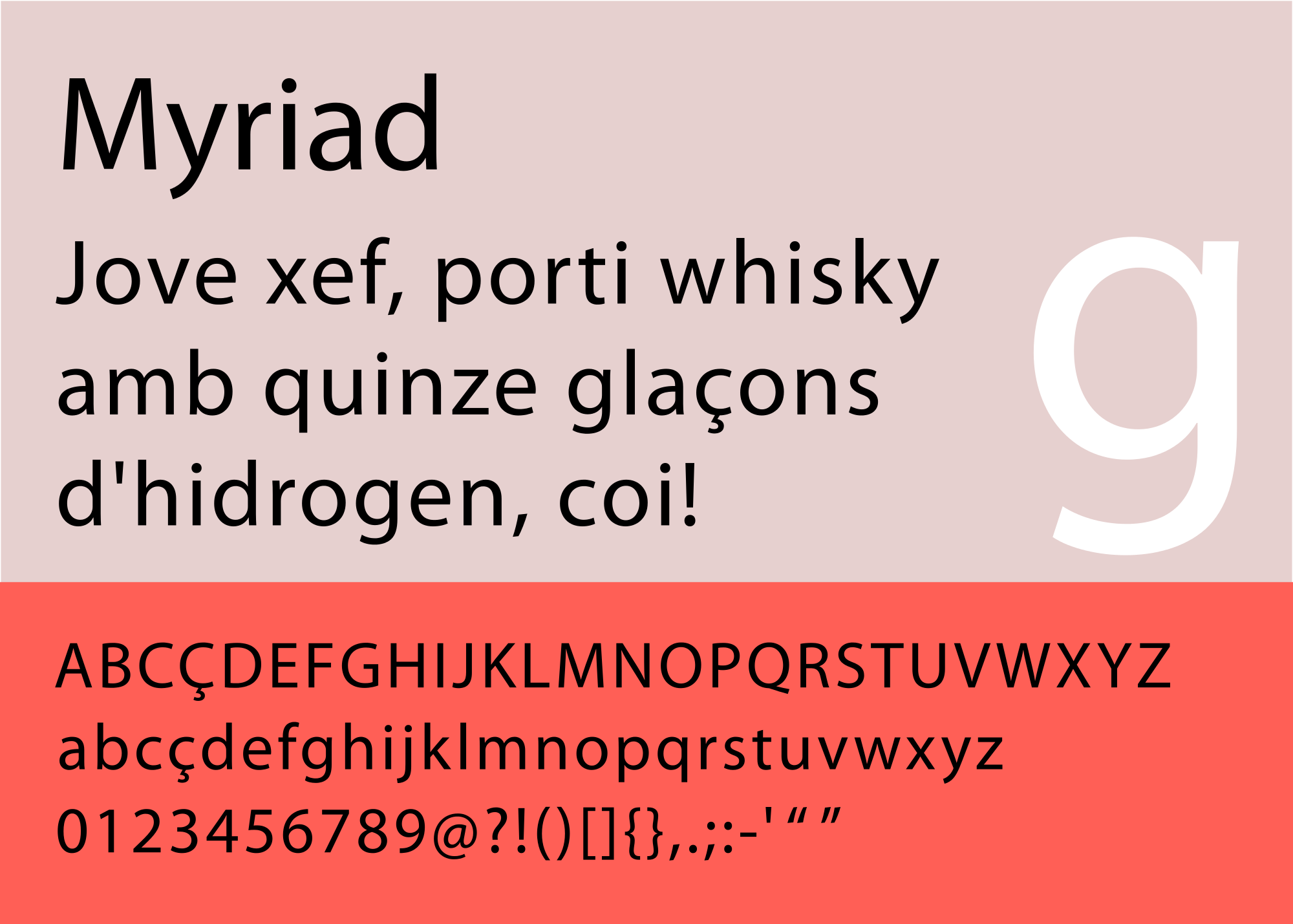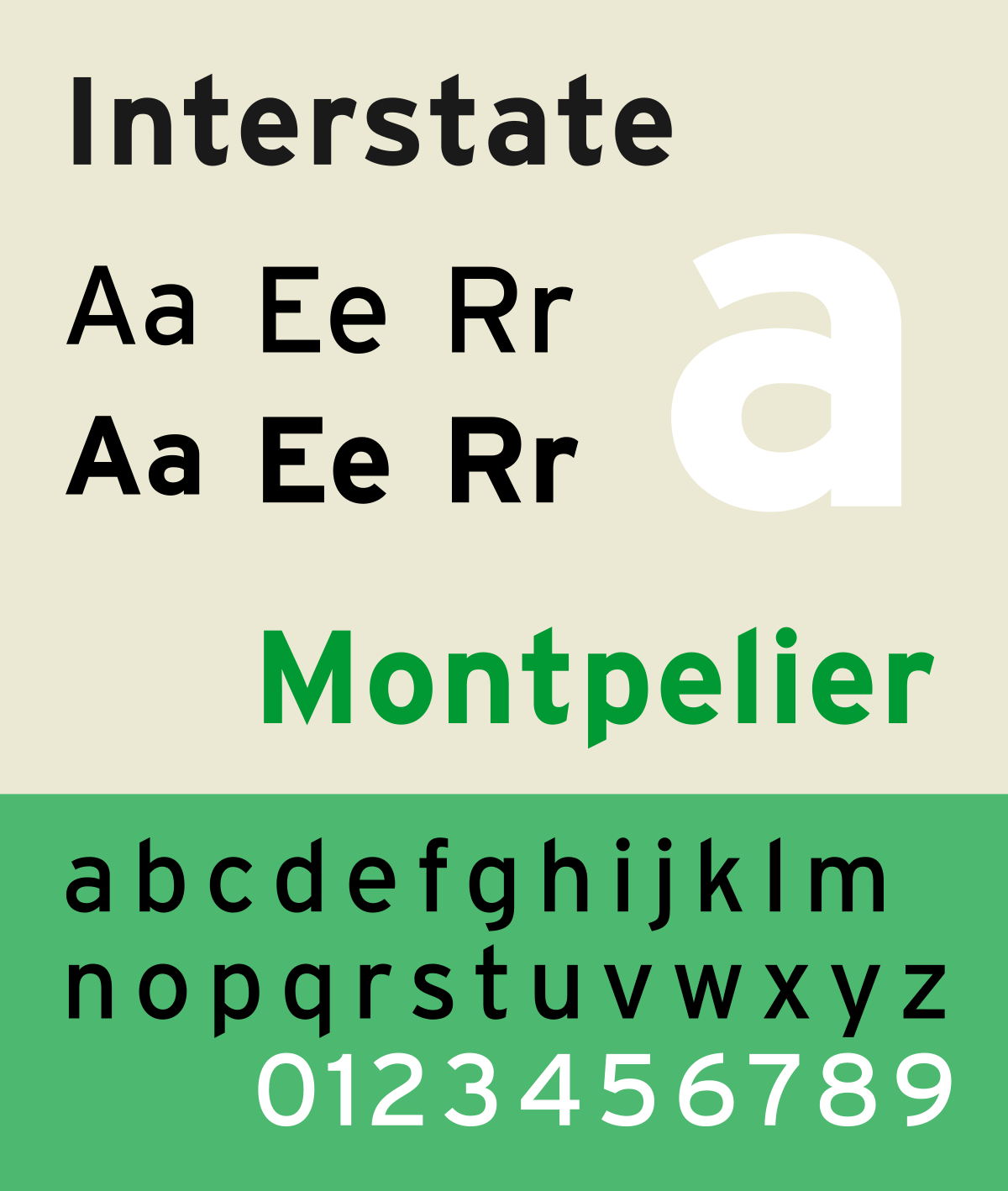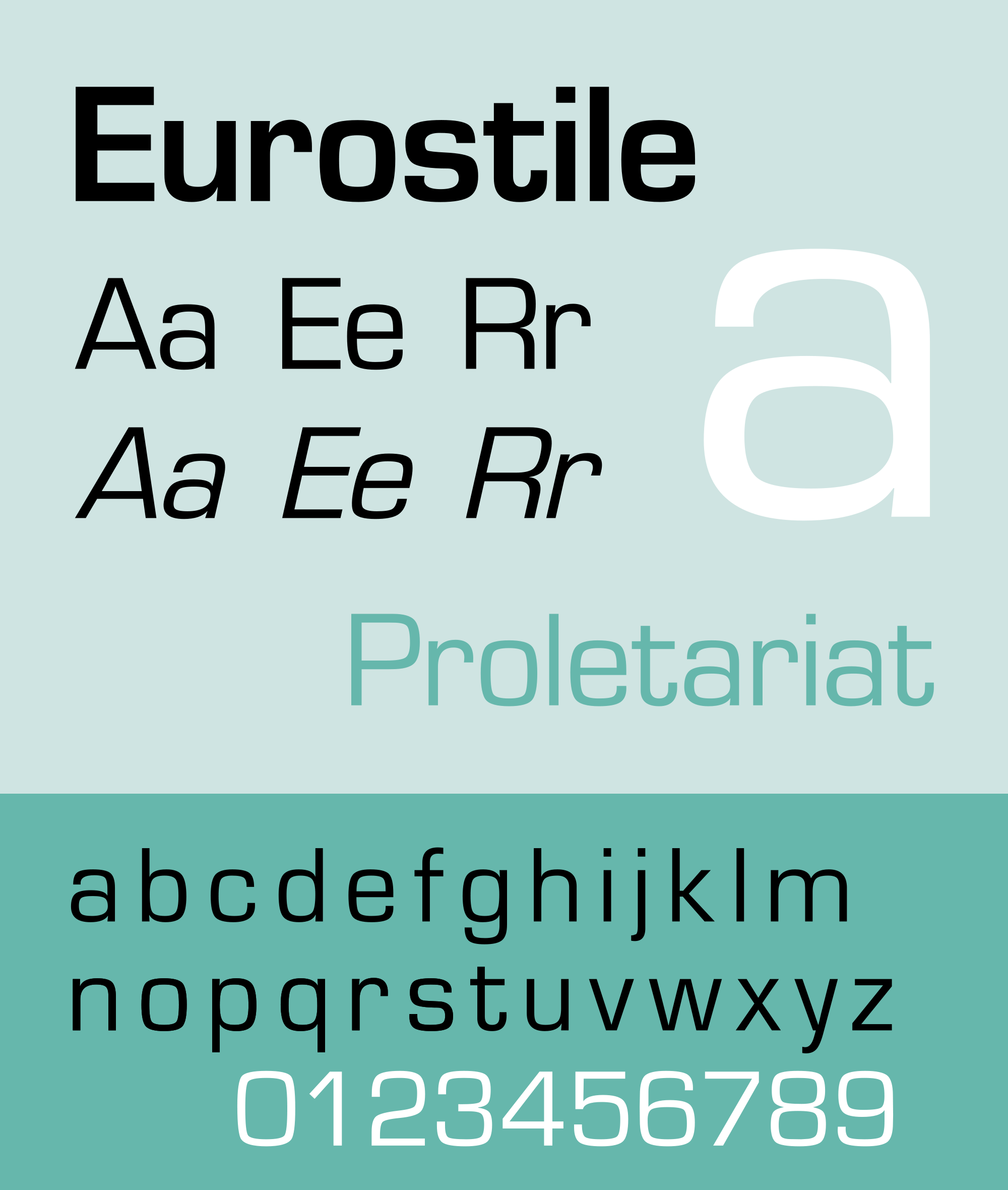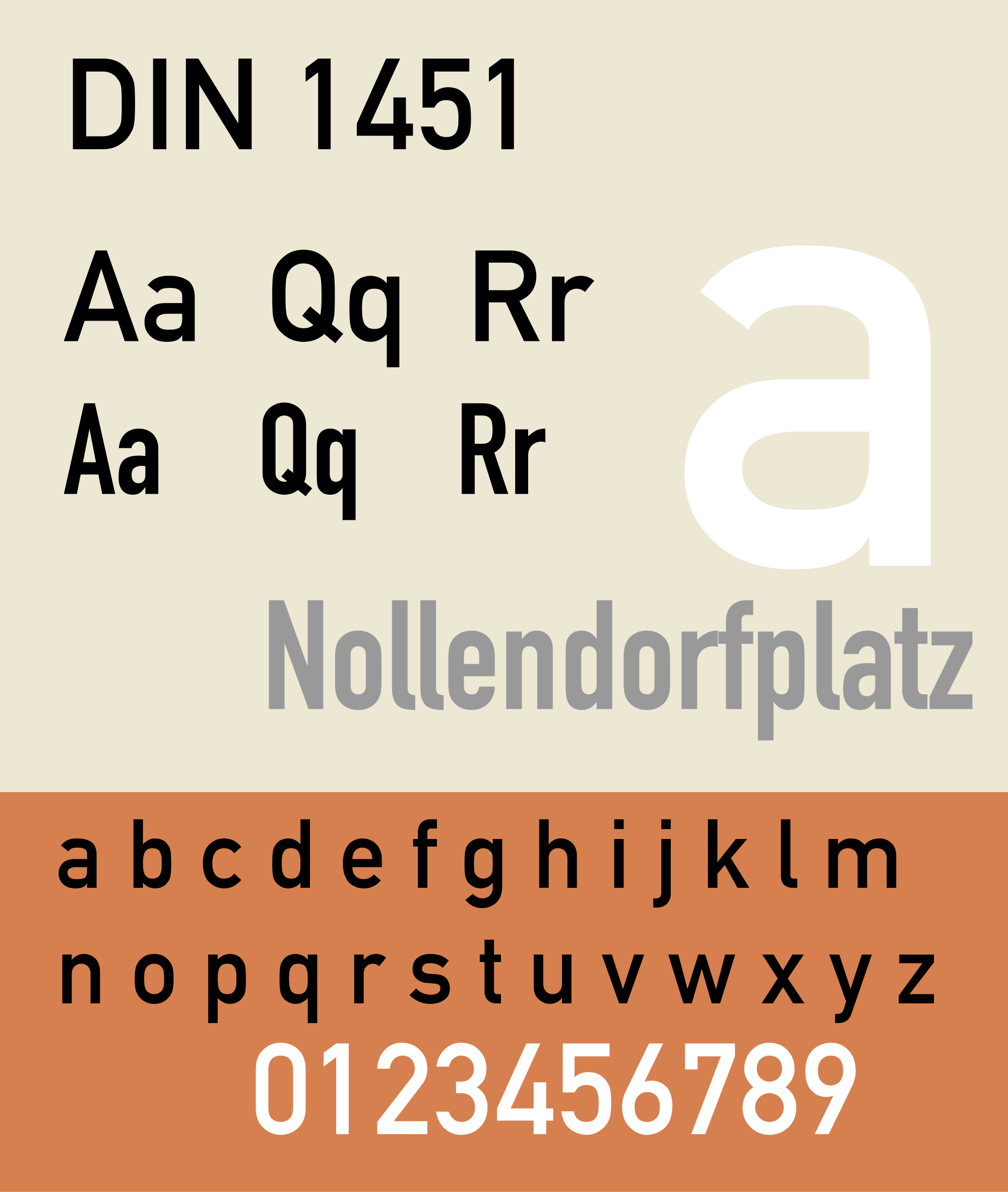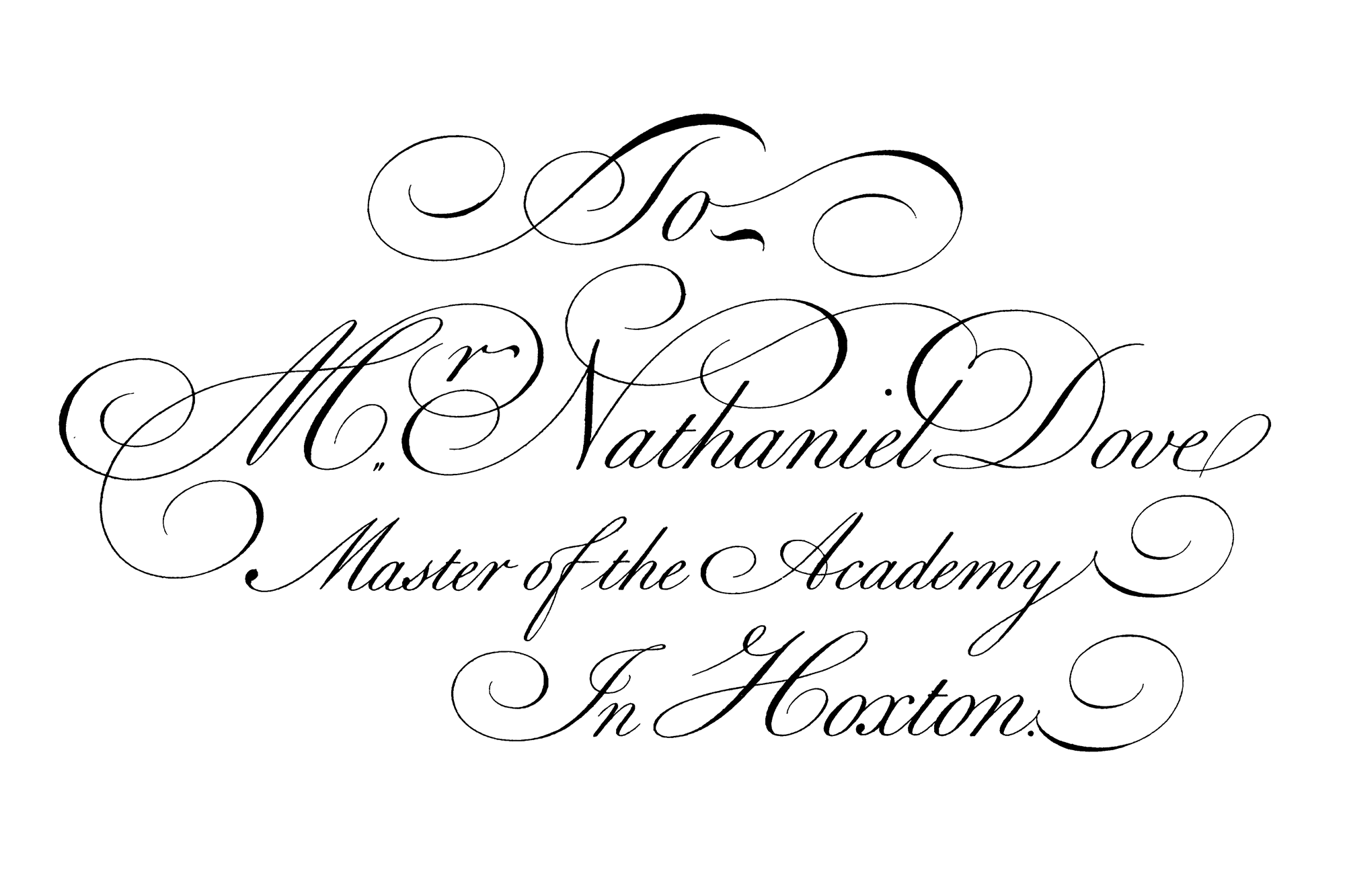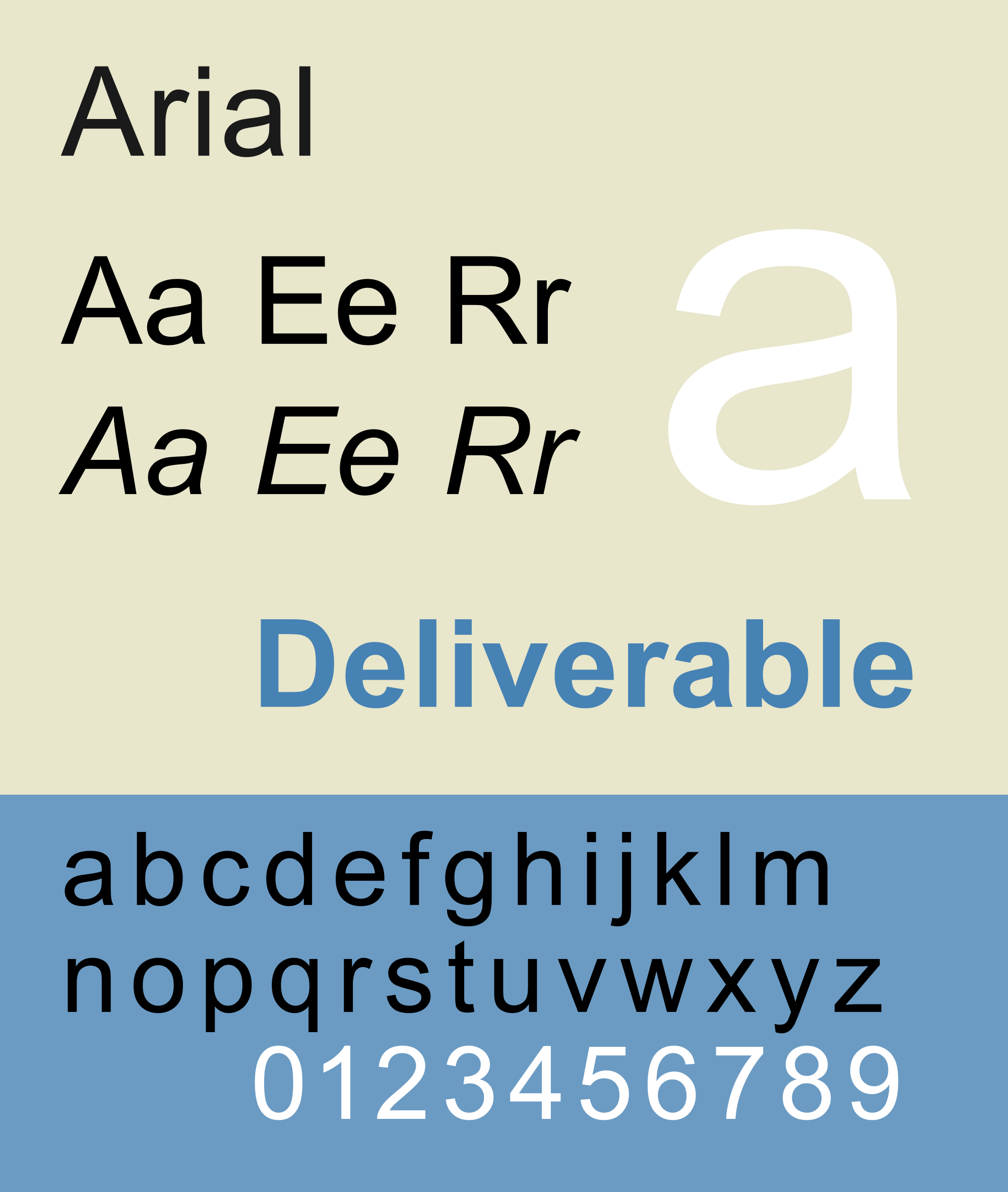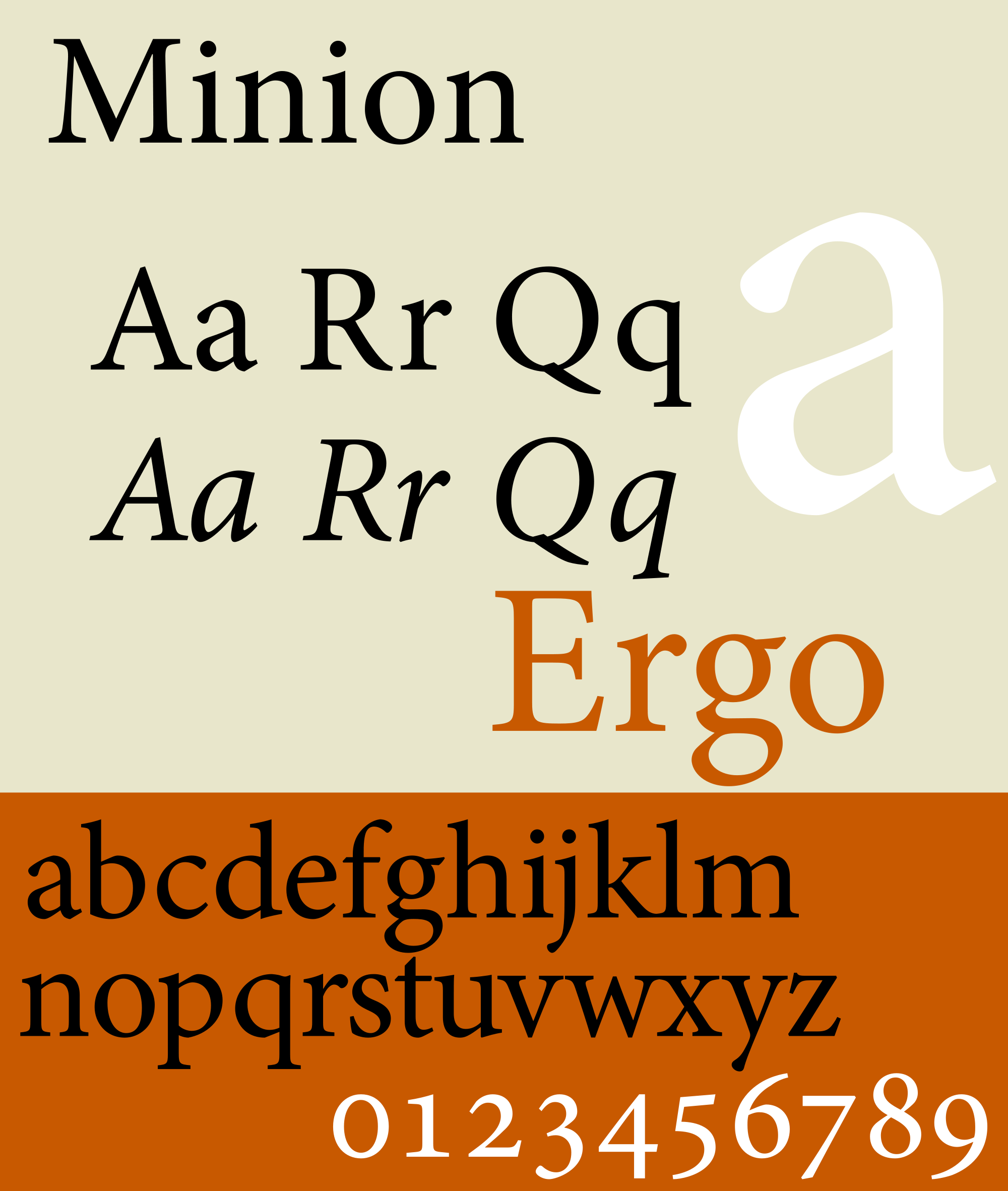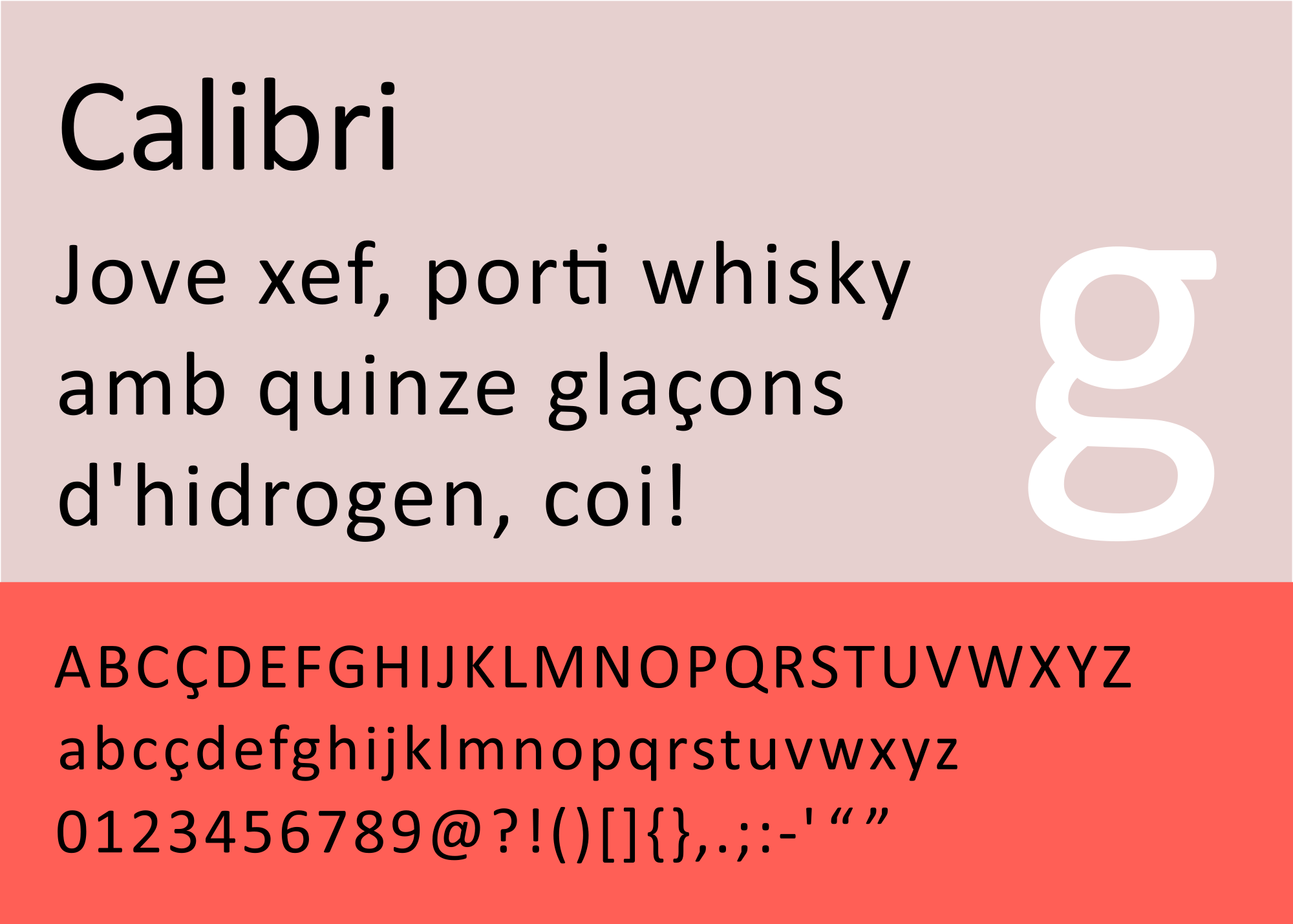
Las 25 tipografías más utilizadas en publicidad
Hay quien dice que un diseño web sin tipografía es un diseño a medias. Pero también se corre el riesgo de elegir la letra incorrecta y estropear todo el diseño. Por ello seguro que te interesa esta selección de las 25 tipografías más utilizadas en publicidad.
No siempre es fácil saber cuál elegir en cada momento. Existen algunas prohibidas, otras recomendadas y otras estándar para diseños sencillos. Pero, ¿con cuál mejoras la apariencia visual de tu sitio web?
Cada tipografía va más allá del simple «arte del texto«. Hacen referencia a la evolución de la creatividad dentro de los diseños web simples y avanzados. Toda arquitectura necesita un apoyo. Y cada web necesita de una tipografía que sirva como apoyo creativo.
Sin embargo no debes quedarte con el concepto de que una tipografía es un mero apoyo. Puede ser la encargada de lograr el éxito en la creación de identidad de la web de la marca. Es un elemento vital, por lo que antes de elegir al azar, deberías saber cuáles son las tipografías más utilizadas en publicidad.
De esta manera podrás tener un listado con las más recomendadas y tú mismo te darás cuenta de que algunas son mucho más limpias y legibles que otras. En la simpleza está la belleza. Deja a un lado las fuentes demasiado complejas. Lo que te interesa es que sea legible.
¿Cuáles son las tipografías más utilizadas en publicidad?
1.- Helvética
tipografía Helvética
La Helvética es una de las tipografías más utilizadas en publicidad y quizás, la más conocida en todo el mundo. Creada en el año 1957 por Max Miedinger y Edouard Hoffmann para la fundición de tipografías. Fue la absoluta protagonista durante los años 60 y 70.
Cuenta con una gran variedad de variantes y es muy versátil en el mundo del diseño. Además, como te hemos dicho lo que nos interesa es dar con tipografías que sean fáciles y claras. Y la Helvética es muy fácil de leer. Es posible que por eso mismo se utilice tanto para crear identidades corporativas.
De hecho aunque se utilice mucho para titulares, su sencillez es la que la convierte en un comodín para innumerables ocasiones.
2.- Bodoni
tipografía bodoni
Bodoni es una tipografía serif diseñada por Giambattista Bodoni en 1798. Su creación culminó 300 años de evolución de la tipografía romana. Tras grandes fusiones entre líneas finas y gruesas surgió esta tipografía.
Actualmente, además de en publicidad este tipo de letra se utiliza mucho en prensa.
3.- Avenir
Las tipografías más utilizadas en publicidad: Avenir
La Avenir es una tipografía clásica diseñada por Adrian Frutiger en 1988. Frutiger fue uno de los tipógrafos más conocidos del siglo XX, y además de la Avenir creó también la Univers.
4.- Univers
Las tipografías más utilizadas en publicidad: Univers
Diseñada también por Frutiger en 1957, la Univers es uno de los mayores éxitos respecto a tipografías de la segunda mitad del siglo XX. Tanto es así que es una de las tipografías más utilizadas en publicidad y en los medios de comunicación.
Es clara, sencilla y legible, por lo que puede darte mucho juego.
5.- Arial
Las tipografías más utilizadas en publicidad: Arial
Sin duda es una de las más conocidas sin serif, es decir, que su terminación es una forma recta, sin adornos. Su boom se dio cuando se incluyó en Windows y a lo largo de los años se ha extendido entre los sitios web y diferentes entornos digitales.
Como consejo, te recomendamos que utilices tipografías sin serif, ya que estas son más fáciles de leer en pantalla.
6.- Futura
Las tipografías más utilizadas en publicidad: Futura
Entre las tipografías más utilizadas en publicidad llegamos a la más famosa del siglo XX, Futura. Este tipo de letra tiene una amplísima gama de cuerpos que abarcan desde las formas más finas hasta las más gruesas.
Se diseñó por Paul Renner en 1925 y tuvo influencia de Bauhaus. Al ser una tipografía muy elegante es ideal para cualquier publicidad, carteles, revistas y libros.
7.- Trajan
Las tipografías más utilizadas en publicidad: Trajan
La Trajan se caracteriza por su diseño antiguo. Y esta característica se debe a que la forma de las letras está inspirada en las inscripciones que tienen las bases de las columnas de Trajano.
Diseñada por Carol Twombly, esta tipografía en un principio se componía únicamente de letras mayúsculas. No obstante, a medida que han ido surgiendo versiones fue avanzando. En 2001 concretamente se proporcionaron también las versalitas para este tipo.
Es una tipografía muy acertada para los contenidos elegantes y selectos.
8.- VAG Rounded
Las tipografías más utilizadas en publicidad: VAG Rounded
Es un tipo de letra geométrico, sans-serif, que fue diseñada como tipografía corporativa de la empresa Volkswagen en 1979. En la actualidad es propiedad de Adobe.
Se suele emplear para publicidad y es una buena opción para los logos, aunque como ves, uno de los más reconocidos ya cuenta con esta tipografía.
9.- Minion
Las tipografías más utilizadas en publicidad: Minion
La Minion es una de las tipografías más utilizadas para publicidad gracias al motivo de su creación. Robert Slimbach la diseñó en 1990 para Adobe, y gracias a su variedad se utiliza para dar vida a diferentes recursos.
10.- Garamond
Las tipografías más utilizadas en publicidad: Garamond
Esta tipografía fue diseñada por Claude Garamond, un impresor de París. Surgió como un pedido. Una vez que Garamond iba cogiendo más y más fama, el rey Francisco I de Francia le encargó la creación de una tipografía con caracteres griegos para publicar la obra «Alphabetum Graecum». Y así surgió la Garamond.
Hoy en día es una de las tipografías más utilizadas en publicidad gracias a una versión que se creó en 1998. Robert Slimbach fue quien le dio un pequeño giro y la convirtió en una letra elegante.
11.- Frutiger
Las tipografías más utilizadas en publicidad: Frutiger
¿Alguna vez te habías parado a pensar en la tipografía que se utiliza para señalizar los aeropuertos? Es muy reconocible. Adrian Frutiger la creó para señalizar el Aeropuerto de Charles de Gaulle, en París. Y aunque en un primer momento se pensó como una fuente sin serif, la familia actual también cuenta con algunos modelos serif.
Es muy común encontrarse con esta tipografía en web y, sobre todo, en logos.
Impulsa tu email marketing con MDirector
Gestiona tus campañas, segmenta a tu audiencia y automatiza correos fácilmente.
¡Convierte tus contactos en clientes!
Precios basados en envíos, no en contactos.
Envía tus campañas sin fraccionarlas.
Servidores europeos con cumplimiento GDPR.
Informes avanzados sin costos extra.
Prueba gratis ahora
La prueba gratuita incluye hasta 5,000 envíos y contactos al mes.
12.- Calibri
Las tipografías más utilizadas en publicidad: Calibri
Calibri es una tipografía predeterminada en el paquete Office de Microsoft desde 2007. Fue la tipografía, creada ex-profeso, para ser empleada como tipografía estándar en su paquete Office. Sustituyó a Times New Roman y a Arial en esta labor. Es una tipografía paloseco, sin ningún tipo de serif u ornamento en su final.
Muy empleada en mensajería instantánea, presentaciones y emailing.
[bannerHero]
13.- Meta
Las tipografías más utilizadas en publicidad: Meta
Creada por Erik Spiekermann a finales de los años 90, la tipografía Meta es increíblemente flexible y apropiada para cualquier publicidad. Es muy popular.
14.- Gill Sans
Las tipografías más utilizadas en publicidad: Gill Sans
¿Sabías que la Gill Sans es la tipografía que se utiliza para el metro de Londres?
Fue creada por el tipógrafo Eric Gill y publicada por la fundición Monotype en el primer tercio del siglo XX. Es una tipografía muy versátil con diferentes versiones.
15.- Myriad
Las tipografías más utilizadas en publicidad: Myriad
La Myriad es un tipo de sans-serif diseñado por Robert Slimbach y Carol Twombly para Adobe Systems. Aunque comúnmente es conocida por ser la tipografía usada por Apple desde 2002.
Uno de los problemas con los que nos encontramos a veces a la hora de elegir tipografía es que nos resulta complicado elegir entre unas y otras. Sobre todo porque no sabemos en qué se diferencian. En el caso de Myriad podemos reconocer este tipo de letra por su descenso de cola en la «y» y su corte en la «e». En los pequeños detalles está la diferencia.
16.- Interstate
Las tipografías más utilizadas en publicidad: Interstate
La Interstate la diseñó Tobias Frere-Jones inspirado en el alfabeto que se utilizaba para la señalización de las carreteras y autopistas en Estados Unidos.
Es muy legible por lo que se utiliza mucho tanto en sitios web como en revistas y periódicos. Una buena elección para dar vida a tus contenidos.
17.- Times New Roman
Las tipografías más utilizadas en publicidad: Times New Roman
Si hablamos de las tipografías más utilizadas en publicidad no puede faltar la Time New Roman. Es una de las primeras tipografías en ser digitalizadas, por lo que está presente en la mayoría de los espacios.
Ya sea para prensa escrita, libros o revistas, este tipo de letra en papel funciona a la perfección. Por lo que si vas a hacer publicidad offline como carteles es una apuesta casi segura.
18.- Clarendon
Las tipografías más utilizadas en publicidad: Clarendon
Esta tipografía la creó Robert Besley en 1845, por lo que es la primera fuente tipográfica registrada.
Como curiosidad te contamos que esta fuente se utilizó mucho durante la Primera Guerra Mundial para las proclamaciones. Y otra de sus características más destacables es que es la típica tipografía que se utilizaba también en los carteles del oeste.
Las tipografías más utilizadas en publicidad: Clarendon
En publicidad se utiliza para dar un toque especial a ciertos contenidos y para hacer anuncios ambientados en ciertos temas. Puede dar mucha personalidad a tus comunicaciones.
19.- Eurostile
Las tipografías más utilizadas en publicidad: Eurostile
Fue diseñada en 1952 por Aldo Novarese y Alessandro Butti. Como puedes ver, el aspecto geométrico cuadrangular de este tipo de letra la convierte en la elección perfecta para publicidades sobre el sector tecnológico.
20.- Franklin Gothic
Las tipografías más utilizadas en publicidad: Franklin Gothic
Su autor, Morris Fuller Benton, es el creador de numerosas tipografías más utilizadas en publicidad hoy en día. La Franklin Gothic se utiliza muchísimo para anuncios y titulares de prensa y cada vez se usa en más proyectos por su amplio abanico de variantes.
21.- Gotham
Las tipografías más utilizadas en publicidad: Gotham
Es quizás una de las tipografías más reconocidas. De hecho una prestigiosa web alemana la situó en el puesto 41 entre las 100 mejores tipografías de todos los tiempos. ¿Sabes cuándo se dio el boom de Gotham? Cuando Obama la escogió para su campaña política.
Como puedes ver las letras más utilizadas y con apariencia más sencilla y legible son las que se llevan la palma.
22.- DIN
Las tipografías más utilizadas en publicidad: DIN
DIN es una de las creaciones más recientes. La creó el diseñador alemán Albert-Jan Pool en 1995.
Es una de las tipografías más utilizadas en publicidad ya que ha pasado a ser una de las elecciones favoritas de muchos diseñadores gráficos.
23.- Cocon
Las tipografías más utilizadas en publicidad: Cocon
Fue Evert Bloemsma quien diseñó esta tipografía en 1998, por lo que pasa a ser otra de las más nuevas.
Puede considerarse a esta tipografía como un tipo de fuente con mucha personalidad y poder. De hecho se utiliza muchísimo en publicidad y, sobre todo para packaging.
24.- Avant Garde
Las tipografías más utilizadas en publicidad: Avant Garde
Cualquier texto que veamos con Avant Garde lo relacionamos directamente con Adidas. Y no es para menos. La marca se encargó de darle el impulso necesario a esta tipografía y ahora es una de las más conocidas y más fácilmente reconocible de todas.
El autor Herb Lubalin diseñó la fuente para la revista Avant Garde Magazine en 1967 y posteriormente se rediseñó en colaboración con Tom Carnase. Fue entonces cuando se añadieron los caracteres de caja baja.
25.- Bickham Script
Las tipografías más utilizadas en publicidad: Bickham Script
Aunque no es precisamente una de las más legibles, la Beckham Script se utiliza mucho para dar un toque especial a los contenidos. Sobre todo para aquellos que estéticamente requieren de una formalidad y estilo clasicista.
Impulsa tu email marketing con MDirector
Gestiona tus campañas, segmenta a tu audiencia y automatiza correos fácilmente.
¡Convierte tus contactos en clientes!
Precios basados en envíos, no en contactos.
Envía tus campañas sin fraccionarlas.
Servidores europeos con cumplimiento GDPR.
Informes avanzados sin costos extra.
Prueba gratis ahora
La prueba gratuita incluye hasta 5,000 envíos y contactos al mes.
Utilizada en un buen contexto puede ser una muy buena elección. No obstante no es recomendable utilizarla para contenidos largos ya que su lectura no es muy cómoda. Esta tipografía es más estética que funcional. Por ello si la escoges debes tener muy claro que deberá ser para ocasiones puntuales.
Como ves existe una gran variedad de tipografías que puedes emplear para resaltar los contenidos de tu sitio web, tu blog o tus anuncios como siempre se ha hecho en la publicidad. Y sobre todo tipografías que te ayudarán a captar leads en tus landing pages.